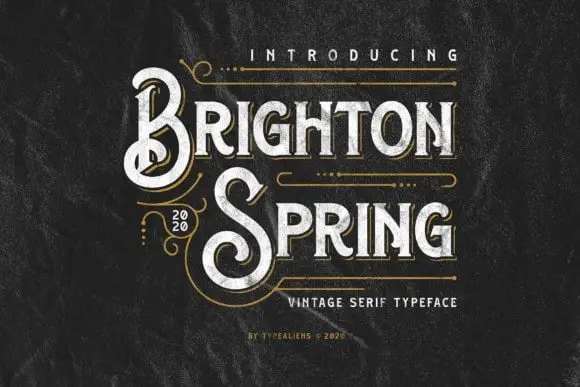
Brighton Spring Display Font – Download Grátis
Na categoria de Fontes Display de 99designs, Brighton Spring Display se destaca por seu estilo moderno que evoca as formas vintage e retro dos produtos antigamente embalados. Esta font possui um design leve e elegante, adaptado para diversas aplicações, desde o branding até os mais detalhados projetos gráficos. Com uma aparência sofisticada e rústica ao mesmo tempo, Brighton Spring é a escolha perfeita para dar um toque único aos seus designs de marca ou newsletter, seja ela em cabeçalhos criativos, design de casamento, cartões de aniversário, assinaturas memoráveis, logotipos únicos ou até mesmo identificações de etiquetas. Seja qual for o projeto que você está trabalhando, Brighton Spring é a fonte perfeita para elevá-lo a um nível superior, garantindo um design impecável e único.